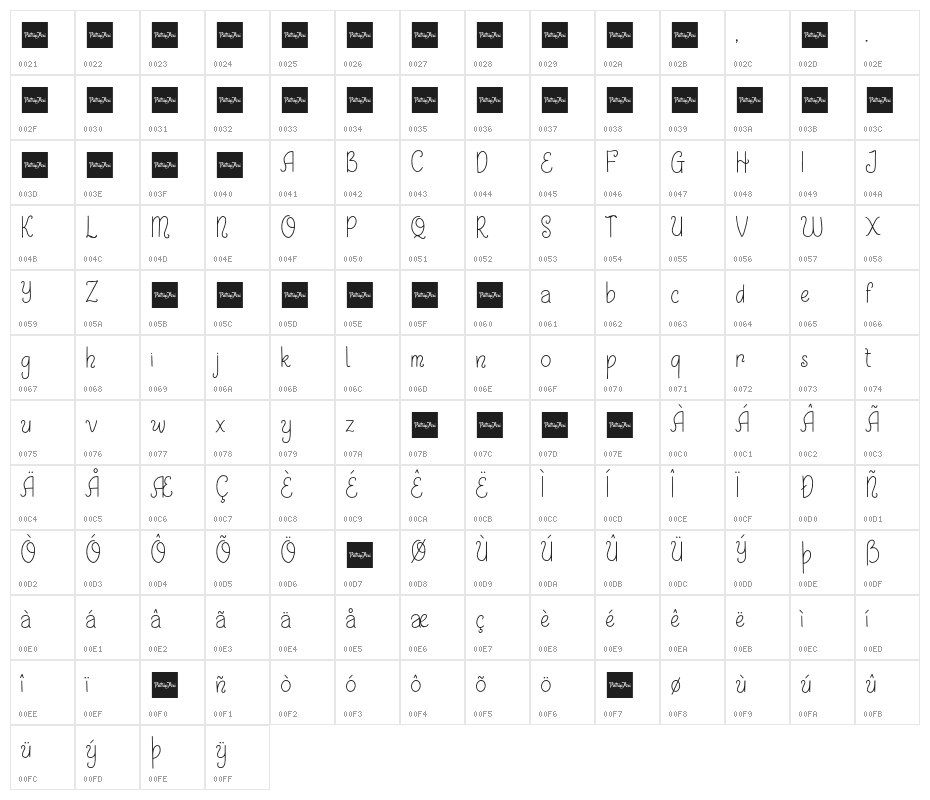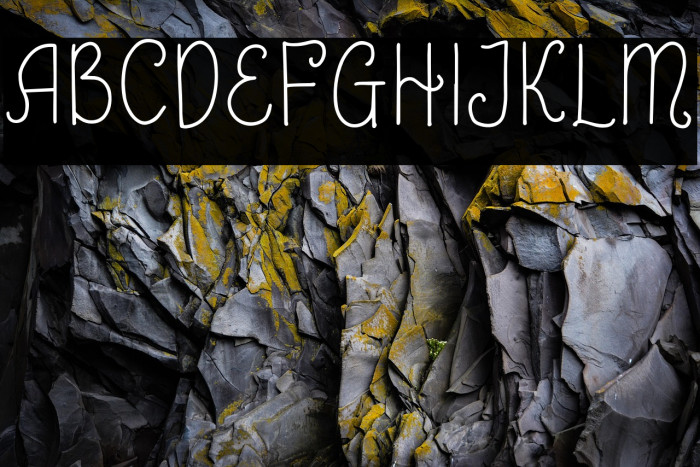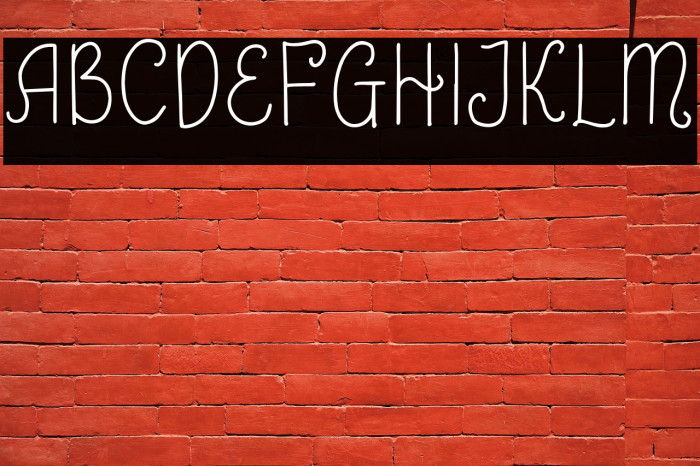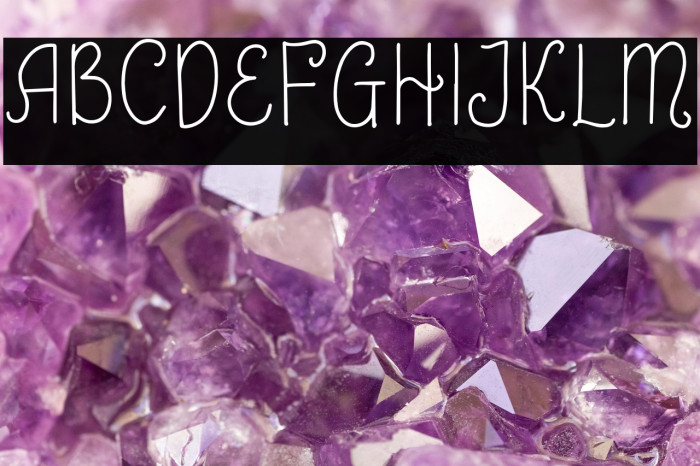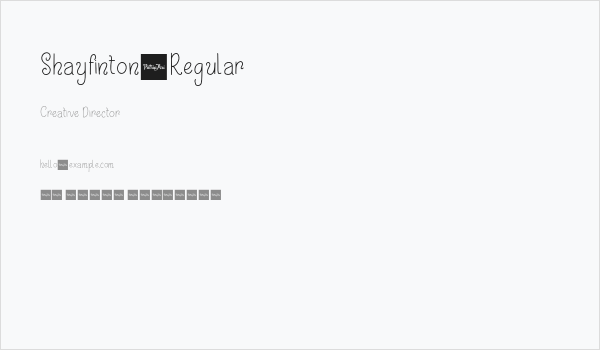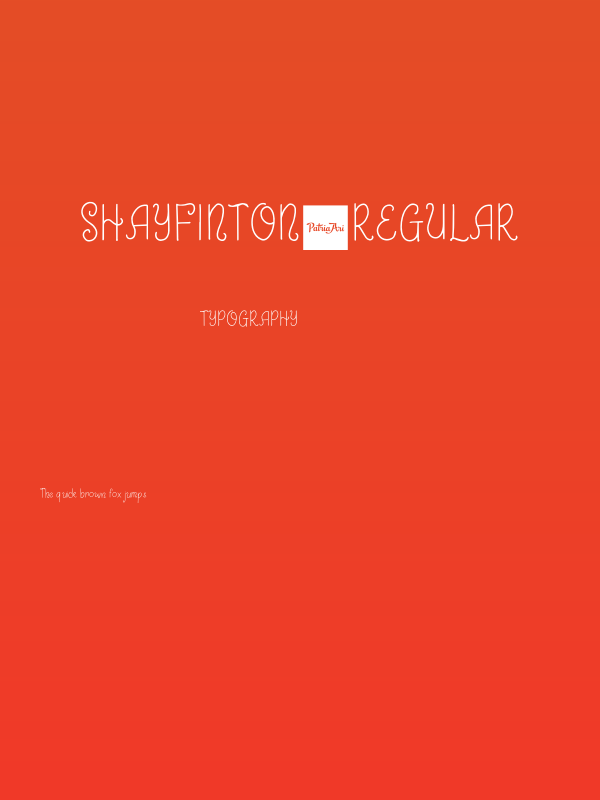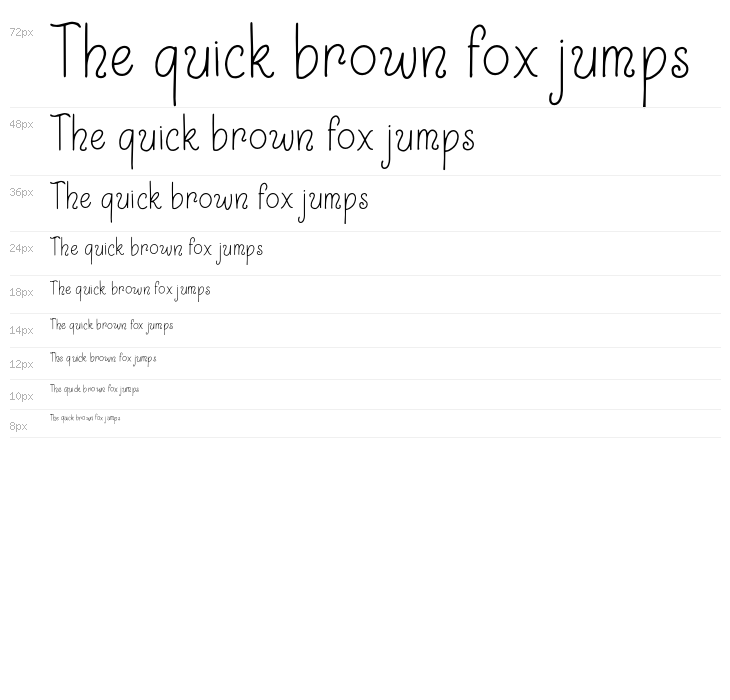
Shayfinton-Regular Font
✎ Curly
| Kategorien | Curly |
| Gesamtstil | Whimsical |
| Anwendungsfall | Headlines, Creative projects, Invitations |
| Vorgeschlagene Projekte | Ideal for greeting cards, invitations, children's books, and creative branding projects. |